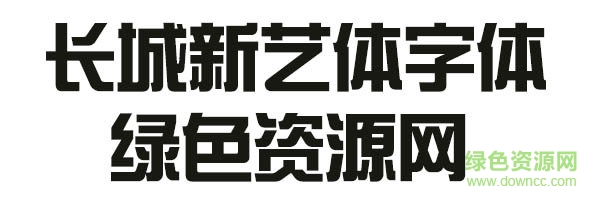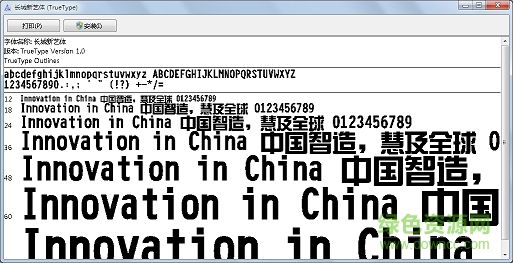
長城新藝體是一款筆畫粗細(xì)一樣,字形方正的簡體字體。該字體整個字形像個方框樣,給人端莊感。喜歡的朋友,趕快到綠色資源網(wǎng)下載體驗吧!
1.看似非常的雄厚、字體很粗
2.適用于藝術(shù)設(shè)計、文檔加粗、廣告突出重點時使。
3.線條粗獷的簡體中文字體,非常的端正厚實
4.以黑體為基礎(chǔ),多了一些圓弧,是字體跳脫出一味的嚴(yán)肅,變得更加靈活。